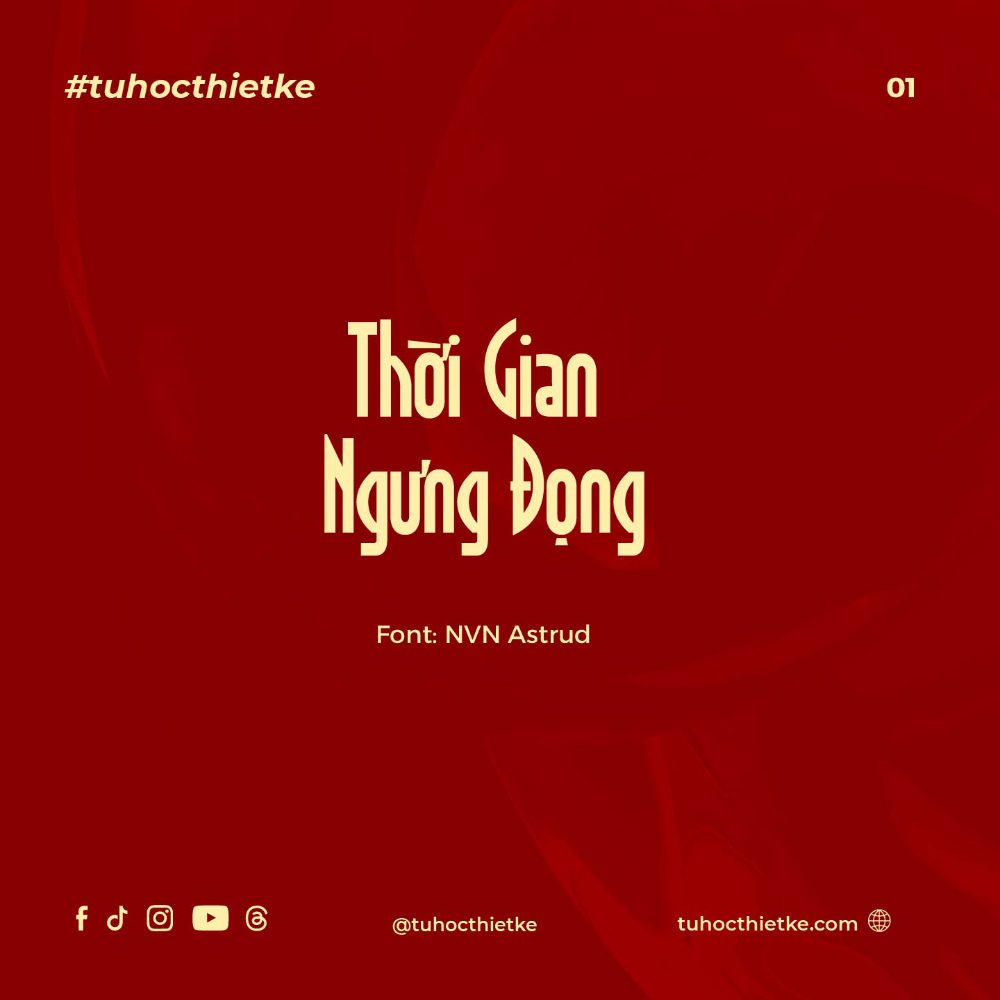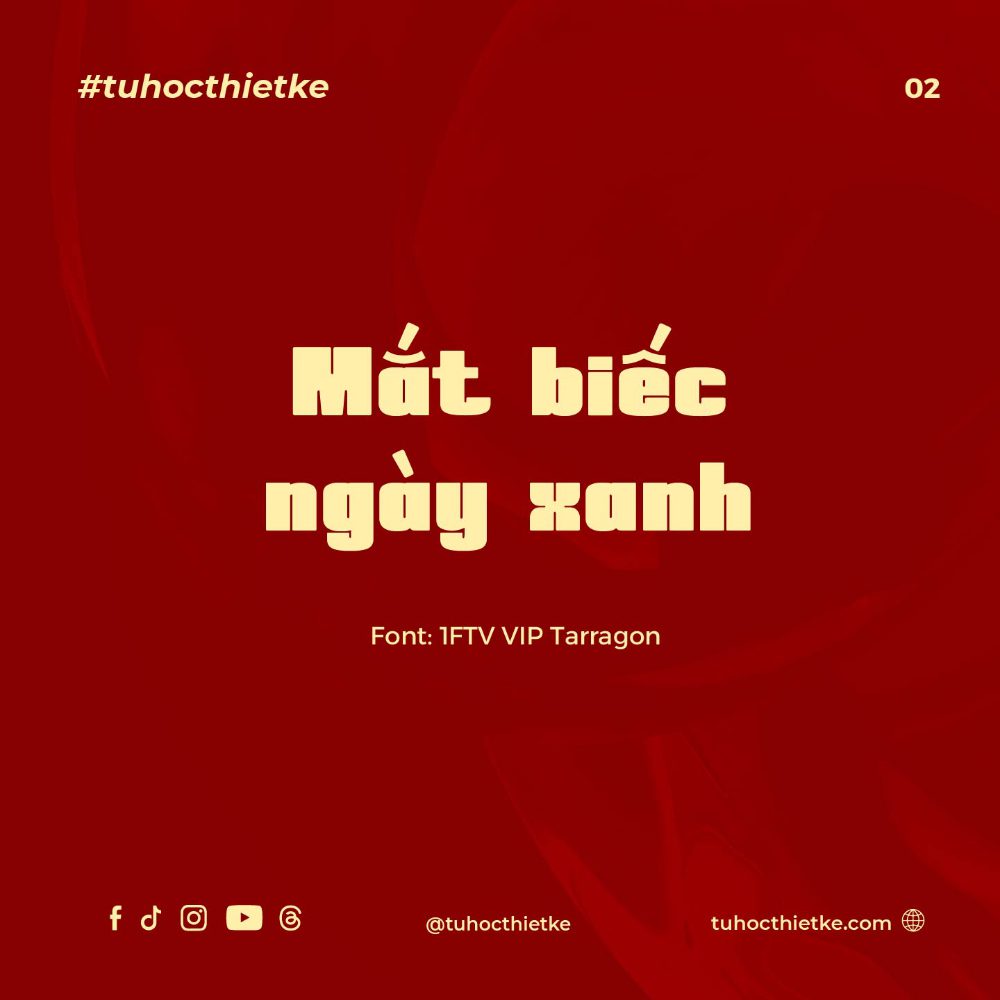
Font Việt hóa Miễn Phí đẹp về thanh xuân là lựa chọn rất phù hợp dành cho designer, content creator, học sinh, sinh viên hoặc những ai đang muốn tạo ra các thiết kế mang cảm xúc trẻ trung, trong trẻo và giàu kỷ niệm. Chủ đề thanh xuân thường gắn liền với tuổi trẻ, trường lớp, bạn bè, những khoảnh khắc đáng nhớ và cảm giác hoài niệm nhẹ nhàng. Vì vậy, việc lựa chọn font chữ phù hợp sẽ giúp thiết kế truyền tải đúng tinh thần, tạo cảm xúc gần gũi và khiến người xem dễ đồng cảm hơn.
Vì Sao Font Chữ Quan Trọng Trong Thiết Kế Về Thanh Xuân?
Trong một thiết kế, font chữ không chỉ dùng để hiển thị nội dung mà còn góp phần tạo nên cảm xúc tổng thể. Với chủ đề thanh xuân, font chữ cần mang lại cảm giác nhẹ nhàng, tươi sáng, gần gũi hoặc đôi khi có chút hoài niệm. Một font chữ phù hợp có thể giúp poster, banner, ảnh bìa, thiệp kỷ yếu, album ảnh hay bài đăng mạng xã hội trở nên có hồn hơn.
Nếu chọn font quá cứng, quá nghiêm túc hoặc không phù hợp với tinh thần tuổi trẻ, thiết kế có thể mất đi sự tự nhiên. Ngược lại, những font có nét mềm mại, dễ đọc, trẻ trung hoặc mang phong cách viết tay sẽ giúp nội dung trở nên cảm xúc và chân thật hơn. Đây là lý do nhiều designer thường dành thời gian tìm kiếm những bộ font đẹp, hỗ trợ tiếng Việt tốt và dễ ứng dụng cho các dự án về thanh xuân.
Font Việt Hóa Miễn Phí Là Gì?
Font Việt hóa Miễn Phí là những bộ font được hỗ trợ tiếng Việt có dấu và có thể tải về sử dụng miễn phí theo điều kiện giấy phép của tác giả. Điểm quan trọng nhất của font Việt hóa là khả năng hiển thị đầy đủ các ký tự tiếng Việt như ă, â, ê, ô, ơ, ư, đ cùng các dấu sắc, huyền, hỏi, ngã, nặng.
Đối với các thiết kế có nội dung tiếng Việt, việc sử dụng font chưa Việt hóa rất dễ gây lỗi dấu, lệch ký tự hoặc mất sự đồng bộ trong bố cục. Điều này đặc biệt ảnh hưởng đến các thiết kế kỷ yếu, poster lớp học, caption ảnh, thiệp cảm ơn hoặc các ấn phẩm mang nhiều câu chữ cảm xúc. Vì vậy, chọn font đã Việt hóa sẽ giúp thiết kế trở nên chỉn chu, dễ đọc và chuyên nghiệp hơn.
Những Kiểu Font Phù Hợp Với Chủ Đề Thanh Xuân
Font viết tay nhẹ nhàng
Font viết tay là lựa chọn rất phổ biến trong các thiết kế về thanh xuân. Kiểu chữ này thường tạo cảm giác gần gũi, tự nhiên và có phần cá nhân hóa, giống như những dòng lưu bút, lời nhắn trong sổ tay hoặc những kỷ niệm được ghi lại bằng cảm xúc thật.
Bạn có thể sử dụng font viết tay cho tiêu đề album kỷ yếu, ảnh bìa, thiệp chia tay, poster lớp học hoặc các câu quote về tuổi trẻ. Tuy nhiên, nên chọn font có độ dễ đọc tốt, tránh những kiểu chữ quá bay bổng hoặc quá nhiều nét nối khiến nội dung bị khó nhìn khi đặt trên ảnh nền.
Font sans-serif trẻ trung
Font sans-serif có nét chữ gọn gàng, hiện đại và dễ đọc. Đây là lựa chọn phù hợp cho các thiết kế cần sự rõ ràng như banner sự kiện, poster trường học, bài đăng mạng xã hội hoặc các nội dung thông báo. Với chủ đề thanh xuân, font sans-serif có thể mang lại cảm giác năng động, sạch sẽ và hiện đại.
Bạn có thể dùng font sans-serif cho phần nội dung phụ, ngày tháng, tên lớp, tên trường hoặc những đoạn mô tả ngắn. Khi kết hợp với font viết tay ở tiêu đề, tổng thể thiết kế sẽ vừa có cảm xúc vừa đảm bảo tính dễ đọc.
Font serif hoài niệm
Font serif có chân thường tạo cảm giác cổ điển, trang trọng và giàu chiều sâu. Với các thiết kế về thanh xuân mang tinh thần hoài niệm, trưởng thành hoặc lưu giữ ký ức, font serif là lựa chọn rất đáng thử. Kiểu font này phù hợp cho các tiêu đề album ảnh, poster kỷ niệm, bìa tập san hoặc các ấn phẩm có phong cách nhẹ nhàng, tinh tế.
Khi dùng font serif, bạn nên kết hợp cùng màu sắc dịu như be, nâu nhạt, xanh pastel, trắng, kem hoặc các tông màu vintage để tạo cảm giác ấm áp và gợi nhớ.
Ứng Dụng Font Việt Hóa Trong Thiết Kế Thanh Xuân
Thiết kế kỷ yếu và album lớp
Kỷ yếu là một trong những dự án sử dụng font về thanh xuân nhiều nhất. Từ bìa album, trang giới thiệu, quote, tên lớp, tên thành viên cho đến lời nhắn cuối cấp, font chữ đều đóng vai trò quan trọng trong việc tạo cảm xúc. Một font đẹp, hỗ trợ tiếng Việt tốt sẽ giúp từng trang thiết kế trở nên chỉn chu và đáng nhớ hơn.
Với album kỷ yếu, bạn có thể kết hợp font viết tay cho các câu quote, font serif cho tiêu đề chính và font sans-serif cho nội dung thông tin. Cách phối này giúp bố cục có điểm nhấn nhưng vẫn dễ đọc và hài hòa.
Thiết kế poster sự kiện học đường
Các sự kiện như lễ tri ân, prom, hội trại, văn nghệ, ngày hội học sinh hoặc chương trình chia tay cuối cấp đều cần những mẫu poster đẹp và đúng tinh thần. Font chữ nên thể hiện được sự trẻ trung, vui tươi hoặc xúc động tùy theo chủ đề sự kiện.
Với những poster mang không khí vui vẻ, có thể chọn font tròn, font sans-serif hiện đại hoặc font display năng động. Với những thiết kế thiên về cảm xúc, font viết tay hoặc serif mềm mại sẽ phù hợp hơn.
Thiết kế social media và quote thanh xuân
Những câu quote về thanh xuân, tình bạn, trường lớp hoặc tuổi trẻ thường được chia sẻ nhiều trên mạng xã hội. Để hình ảnh quote trở nên thu hút, font chữ cần dễ đọc và phù hợp với cảm xúc của câu chữ.
Khi chọn font, hãy ưu tiên độ dễ đọc, khả năng hiển thị tiếng Việt, phong cách phù hợp với chủ đề và giấy phép sử dụng rõ ràng. Một bộ font được chọn lọc kỹ không chỉ giúp thiết kế đẹp hơn mà còn giúp câu chuyện thanh xuân được truyền tải một cách tự nhiên, chân thành và đáng nhớ.